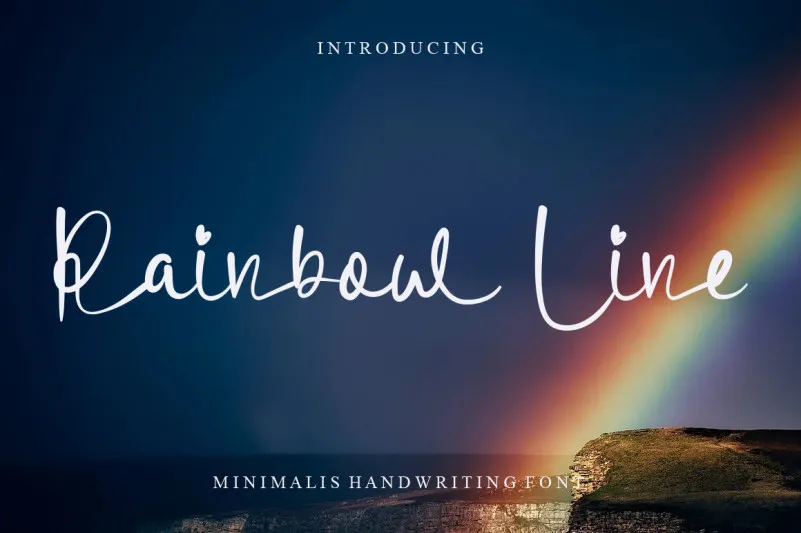
Rainbow Line Font – Download Grátis
A Rainbow Line Font é uma elegante fórmula de escrita cursiva genuína que se destaca por sua delicadeza e naturalidade. Ideal para designers buscando adicionar um toque amigável e romântico a seus projetos, esta fonte garantirá resultados incríveis em diversas ideias gráficas. Seja ela incorporada a editoriais de texto ou utilizada como título em designs digitais, essa fonte manterá sua identidade única ao mesmo tempo que adicionará um toque suave e acolhedor aos seus trabalhos. A Rainbow Line Font é uma escolha perfeita para designers que buscam dar vida às suas criações com um toque delicado, garantindo um resultado vibrante e alegre em cada projeto. Com sua rica tipografia e versatilidade de uso, ela se torna uma fonte indispensável para qualquer designer buscando introduzir nuances ao seu trabalho gráfico.